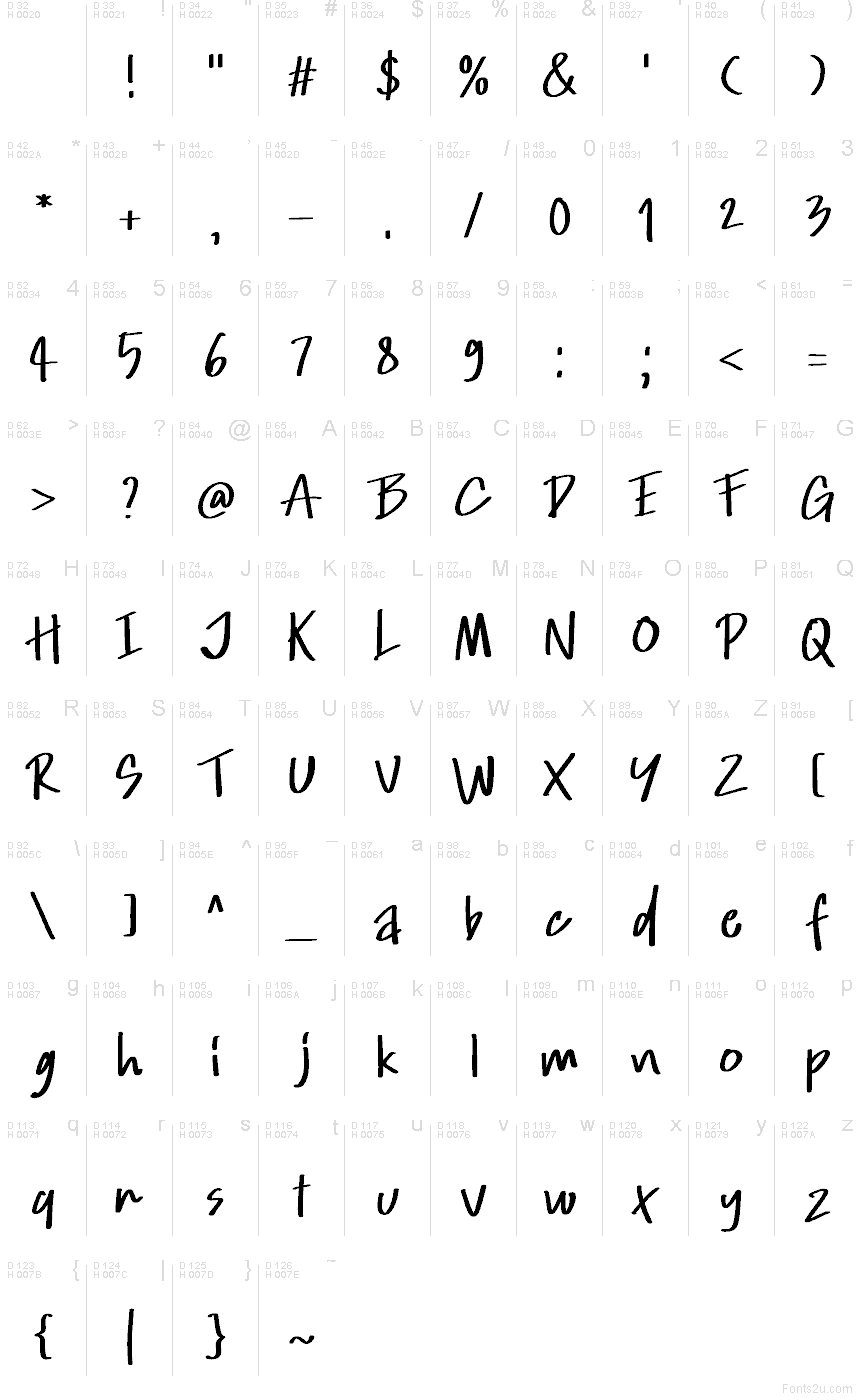
Rindang Alam
Rindang Alam, créée par Hello Good Studio, est une police manuscrite gratuite aux traits souples, façon pinceau, portée par un rythme décontracté et légèrement irrégulier. Les lettres conservent un aspect dessiné à la main, avec des courbes arrondies et des formes simples qui confèrent à l’ensemble une allure informelle sans jamais paraître négligée.
Rindang Alam est idéale pour les logos, les citations graphiques, le packaging, les réseaux sociaux, les invitations et les affiches, car son style apporte une touche personnelle et directe. Elle insuffle un esprit manuscrit aux textes courts, où ses formes relaxées permettent de créer une identité de marque conviviale ou un titre décoratif chaleureux.